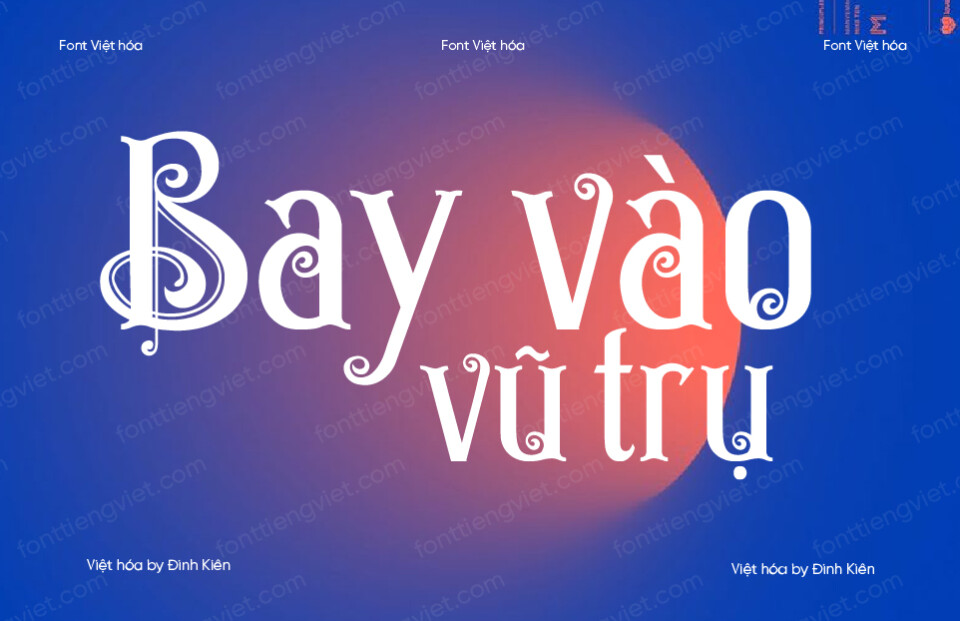
Giới thiệu về Font Việt hóa UTM Egorycastle trong thiết kế
Trong thế giới đồ họa hiện đại, việc lựa chọn một Font Chữ phù hợp đóng vai trò quyết định đến thẩm mỹ của toàn bộ tác phẩm. Font Việt hóa UTM Egorycastle là một trong những bộ font thuộc bảng mã Unicode phổ biến, nổi bật với phong cách mạnh mẽ nhưng không kém phần tinh tế. Đây là sự lựa chọn hoàn hảo cho những ai đang tìm kiếm sự chuyên nghiệp trong các bài thuyết trình, ấn phẩm trường học hay các dự án cá nhân cần sự nghiêm túc và đẳng cấp. Nhờ việc được việt hóa chỉn chu, người dùng có thể dễ dàng sử dụng các ký tự tiếng Việt có dấu mà không lo lỗi font hay sai lệch hiển thị.
Đặc điểm nổi bật của Font Việt hóa UTM Egorycastle
Bộ Font Việt hóa UTM Egorycastle sở hữu các đường nét dứt khoát, hình khối rõ ràng, giúp văn bản trở nên dễ đọc và bắt mắt ngay từ cái nhìn đầu tiên. Đối với các bạn học sinh và giáo viên, font chữ này cực kỳ hữu ích khi làm bìa báo tường, thiết kế slide giảng dạy hoặc trang trí các chứng nhận khen thưởng. Tính ứng dụng cao của nó còn trải dài từ thiết kế logo đến in ấn banner quảng cáo. Bạn có thể kết hợp font này với các kiểu chữ mềm mại hơn để tạo nên sự tương phản độc đáo, giúp thông điệp truyền tải trở nên ấn tượng và sâu sắc hơn trong mắt người xem.